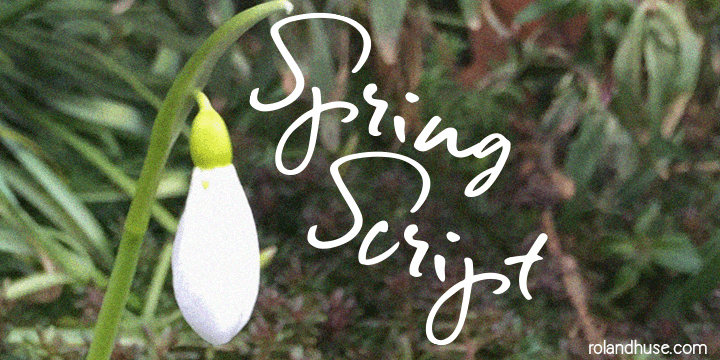
Spring Script Font é uma elegante caligrafia semifeitiçada que traz à tona a essência do estilo handwritten com um toque um pouco desorganizado, oferecendo uma diversidade única de texturas e formas. Embora algumas palavras possam não alcançar sua melhor forma em todas as configurações, muitas se destacam perfeitamente para nomes de marca e títulos grandes. Esta fonte é especialmente versátil quando usada em maiúsculas, mantendo uma consistência visual impressionante mesmo sem o desafio da proporção da letra minúscula. Hamilton, designer nessa categoria especial, criou esta fonte para aqueles que buscam um equilíbrio entre originalidade e facilidade de uso, permitindo experimentar seus incríveis resultados sem comprometer a estética ou a legibilidade do texto. Seja você uma marca atenta aos detalhes ou um designer procurando por personalidade em cada palavra escrita, o Spring Script Font está à sua disposição para dar vida ao seu projeto.